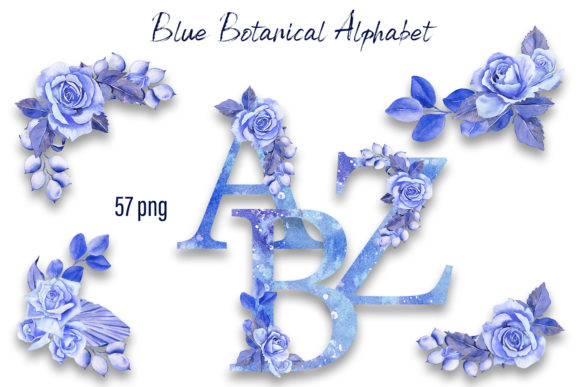
Blue Floral Rose Botanical Alphabet
Trouver les bons éléments de conception peut être un défi, mais Blue Floral Rose Botanical Alphabet propose une collection exceptionnelle qui rehausse instantanément votre travail.
Que vous créiez des produits POD (impression à la demande), des invitations de mariage ou des visuels pour les réseaux sociaux, Blue Floral Rose Botanical Alphabet est un choix idéal.